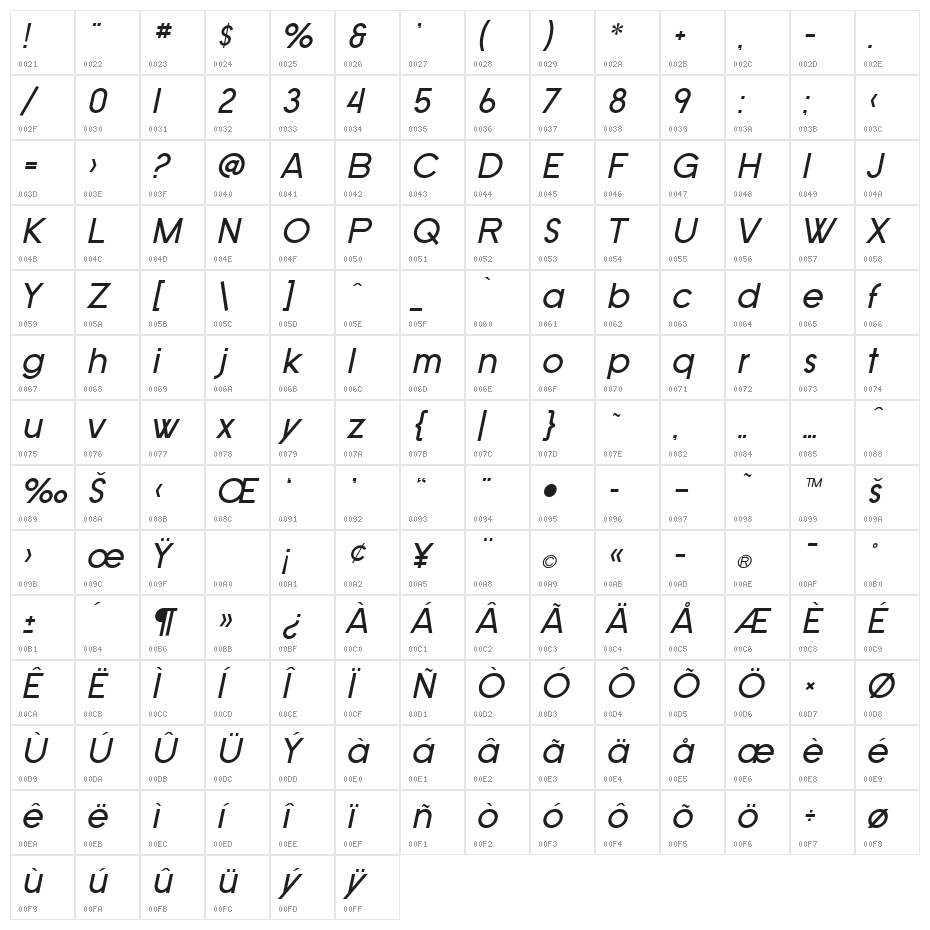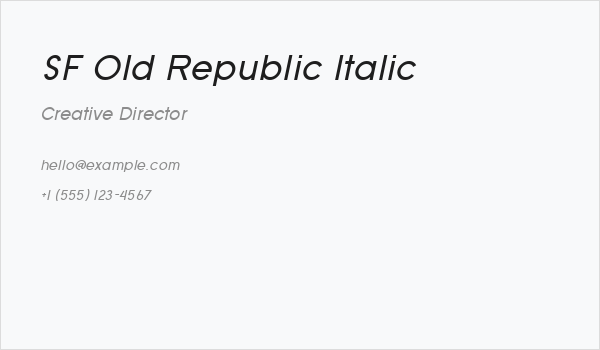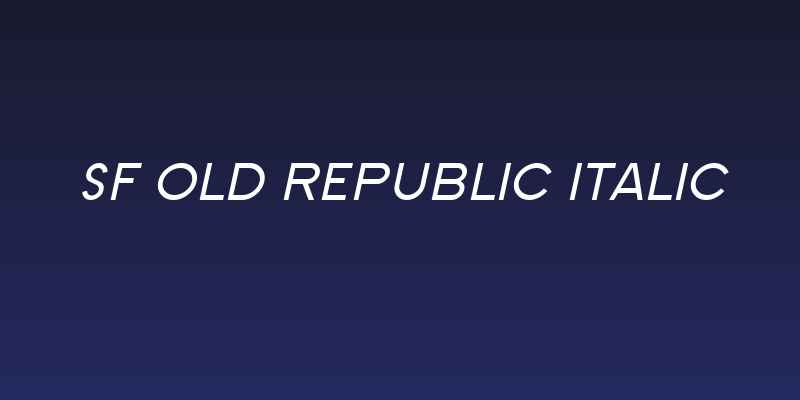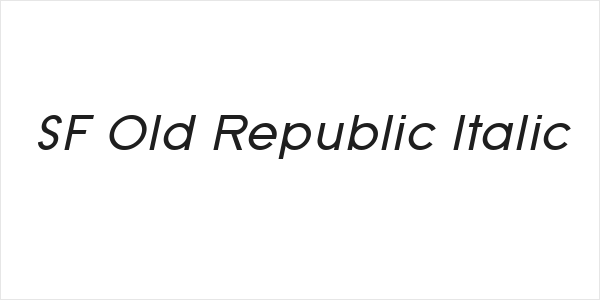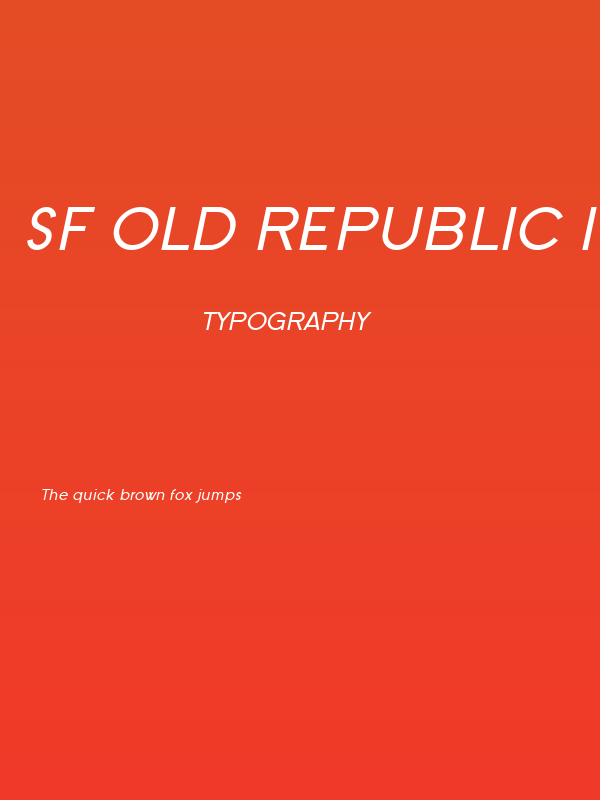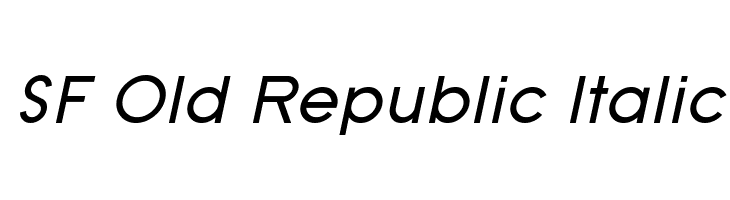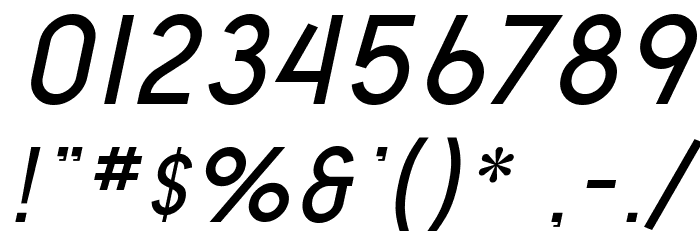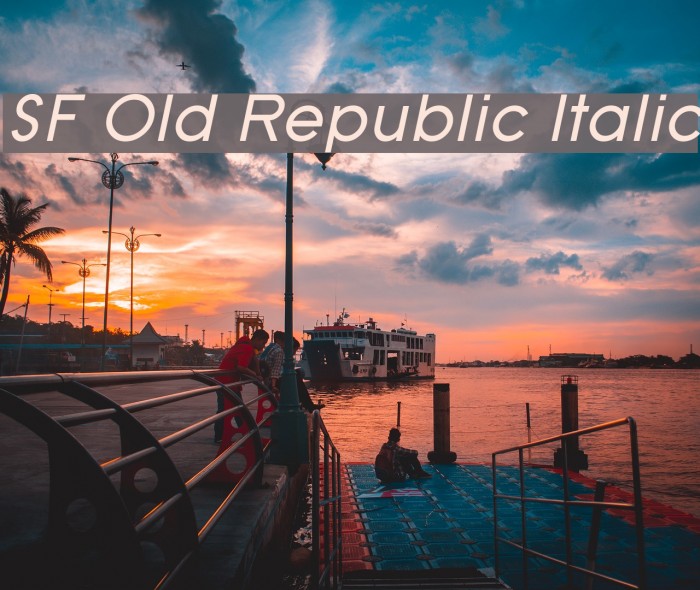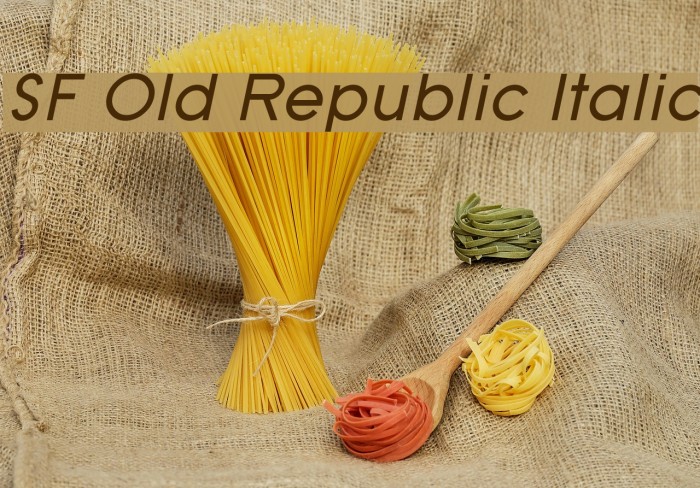
SF Old Republic Italic Font
| Anwendungsfall | Headlines, Logos, Editorial design |
| Vorgeschlagene Projekte | Ideal for branding, advertising, and editorial design projects. Suitable for use in logos, headlines, and promotional materials. |